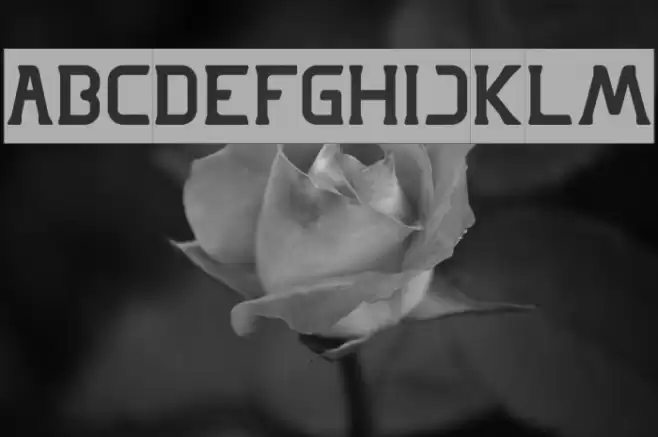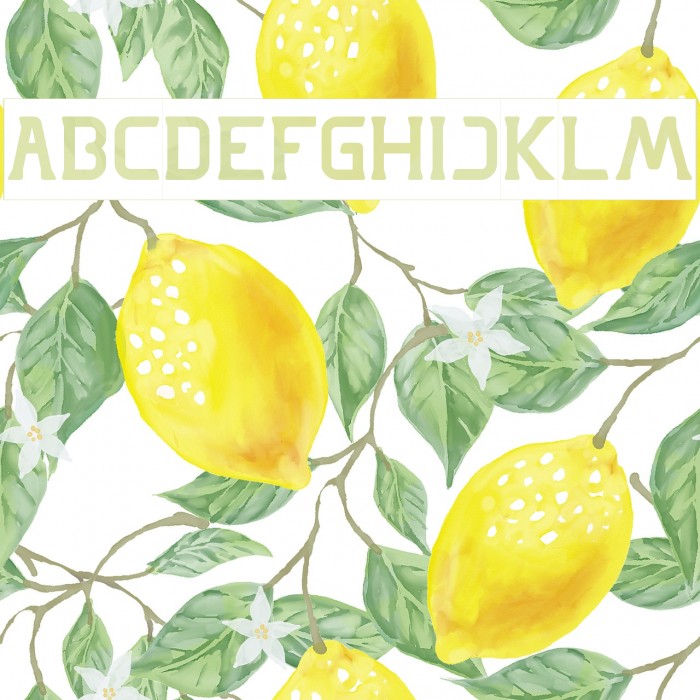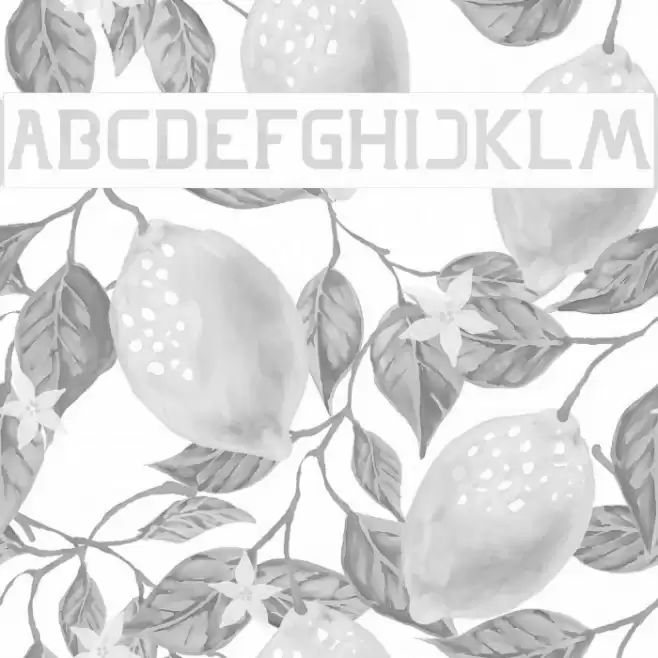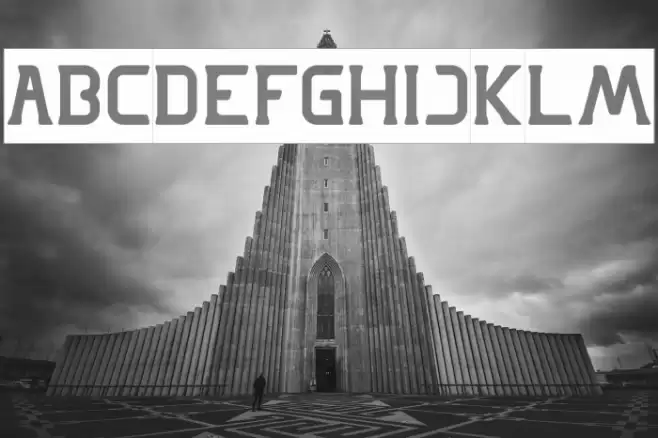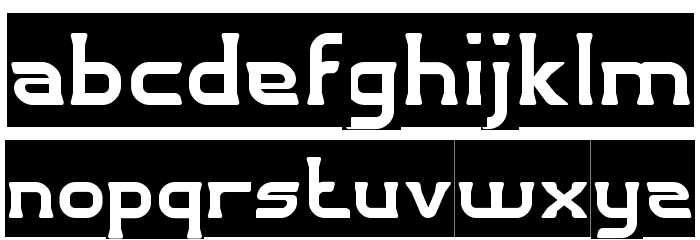
GREAT ADVENTURE-Inverse Font
weknow - Wino S Kadir - www.creativefabrica.com/designer/weknow/
| 全体的なスタイル | Modern, Adventurous |
| おすすめプロジェクト | Ideal for branding, posters, headlines, and any project requiring a bold, impactful typeface. |